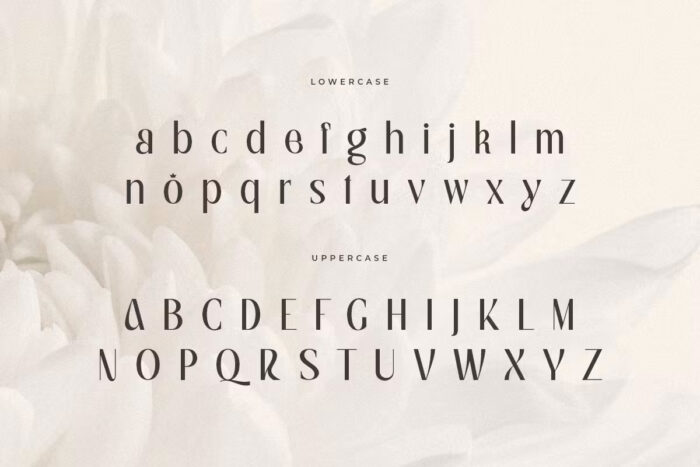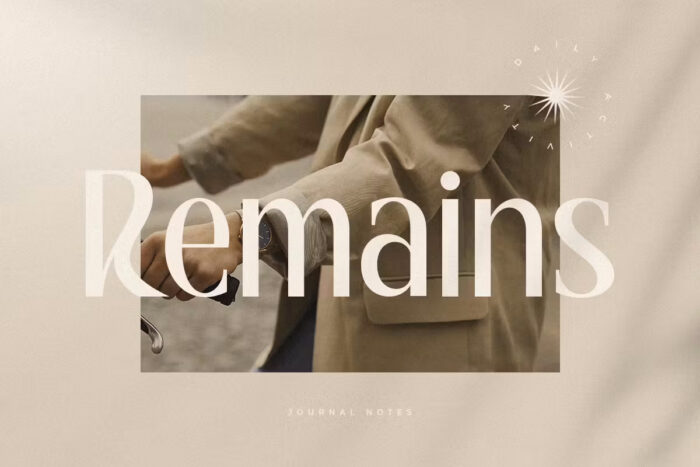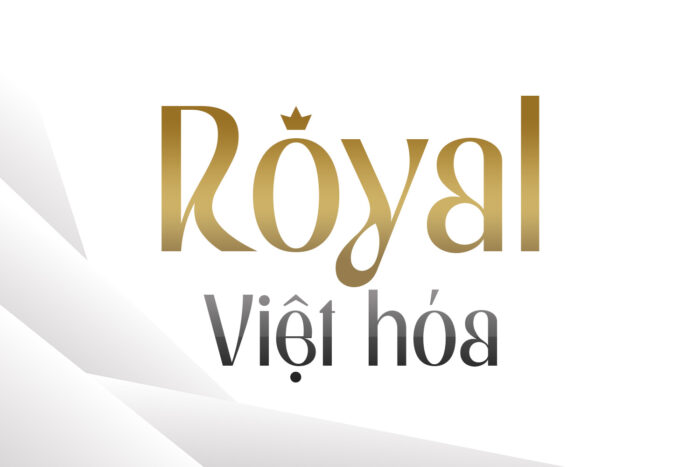
DVN Royal Việt hóa – Font chữ Serif sang trọng, phong cách hoàng gia
Font chữ DVN Royal mang phong cách Serif với nét thiết kế tinh tế và sang trọng. Điểm đặc biệt của font chữ này là sự kết hợp giữa đường nét cổ điển và hiện đại, tạo nên sự uyển chuyển và lịch lãm. Những đường cong mềm mại cùng với chi tiết nhỏ, như chiếc vương miện trên chữ “o”, góp phần tạo nên vẻ đẹp hoàng gia và sự đẳng cấp.
Font chữ DVN Royal thích hợp cho các thiết kế cần sự trang trọng và cao cấp như thiệp mời, logo, tiêu đề sách, và các ấn phẩm quảng cáo sang trọng. Khả năng Việt hóa giúp font chữ này dễ dàng tiếp cận và sử dụng trong các dự án tại Việt Nam, mang lại sự đồng bộ và hài hòa về ngôn ngữ và thẩm mỹ. Bên cạnh đó, DVN Royal còn phù hợp cho các bài thuyết trình hoặc các dự án đòi hỏi sự chuyên nghiệp và ấn tượng mạnh mẽ.
Nhờ vào sự kết hợp tinh tế giữa truyền thống và hiện đại, DVN Royal chắc chắn sẽ là lựa chọn lý tưởng cho những ai muốn tạo dấu ấn đặc biệt trong các thiết kế của mình.